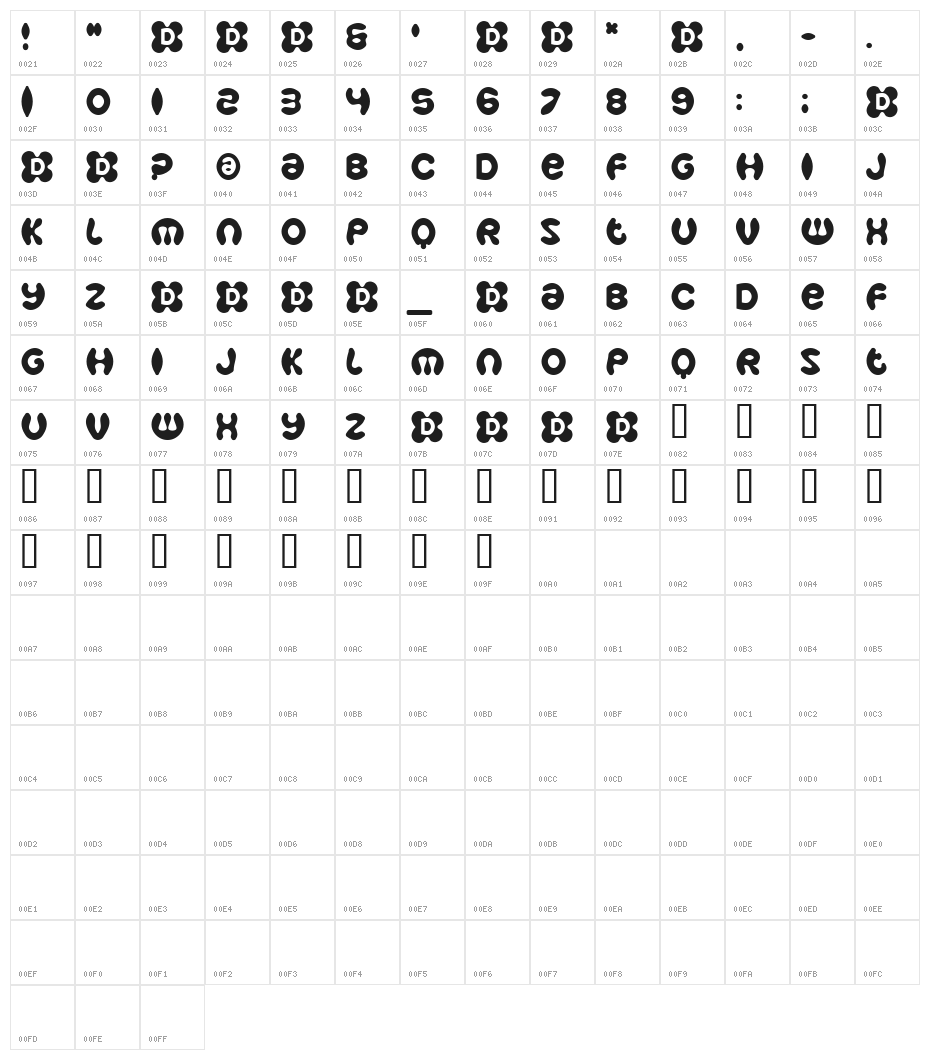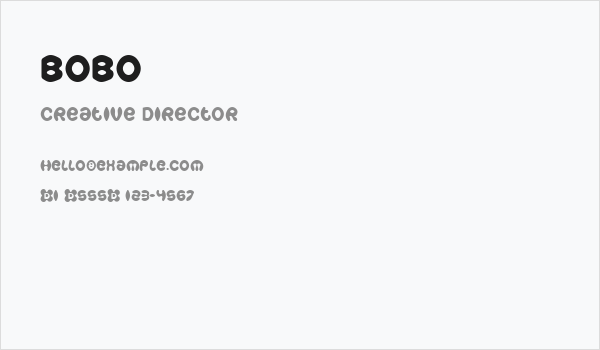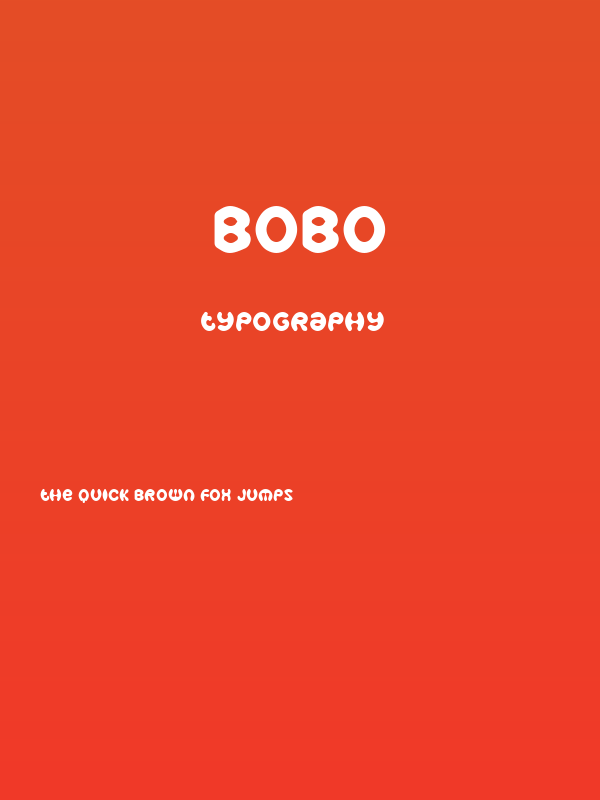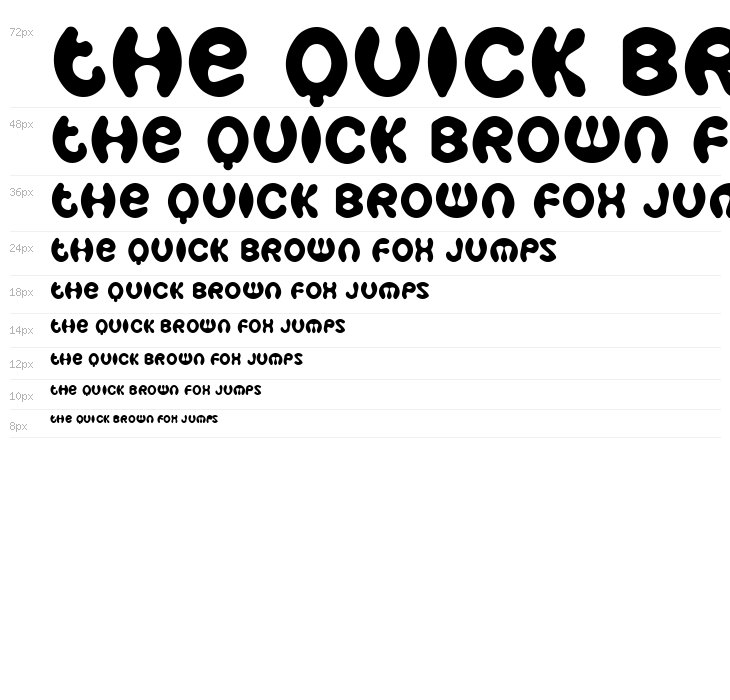
Bobo Font
| Estilo general | Playful, Whimsical, Decorative |
| Caso de uso | Logos, Headlines, Posters |
| Proyectos propuestos | Ideal for children's books, playful branding, party invitations, and creative posters. |